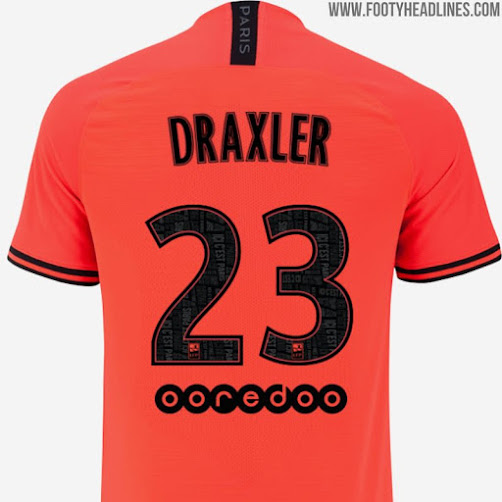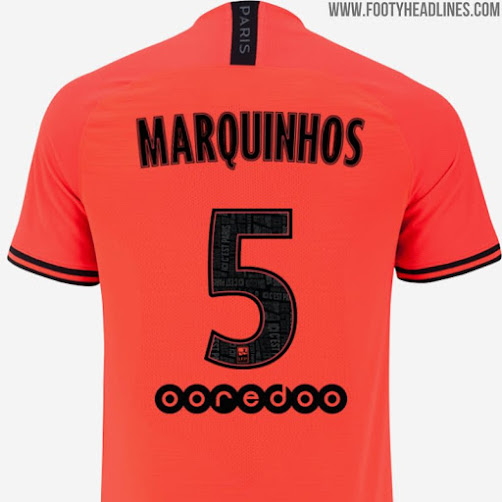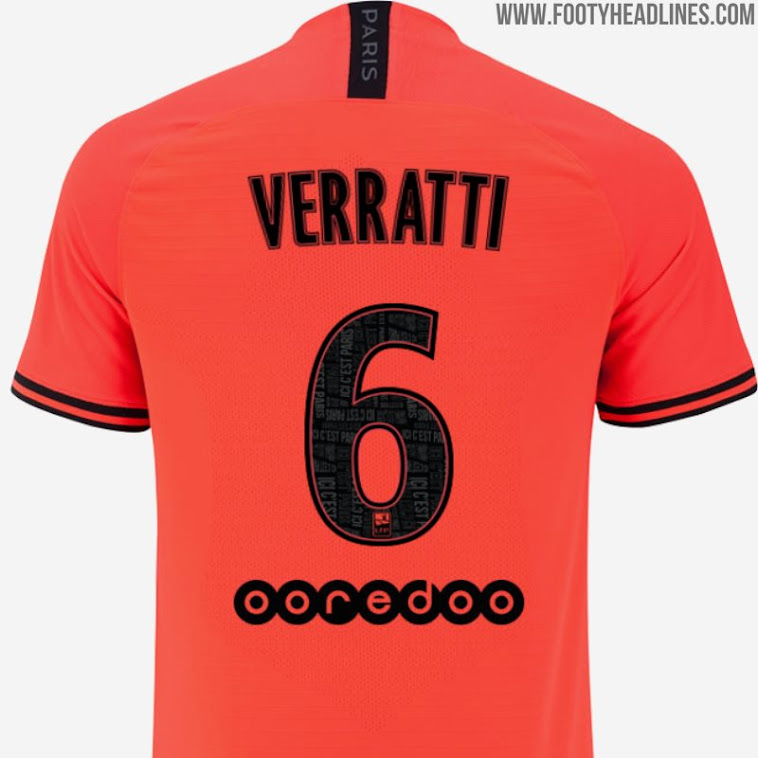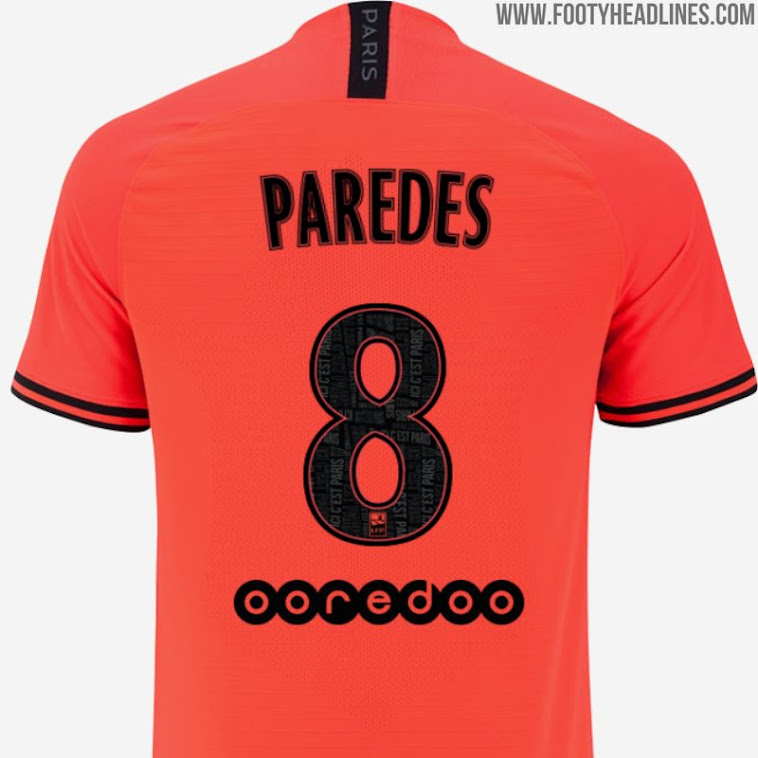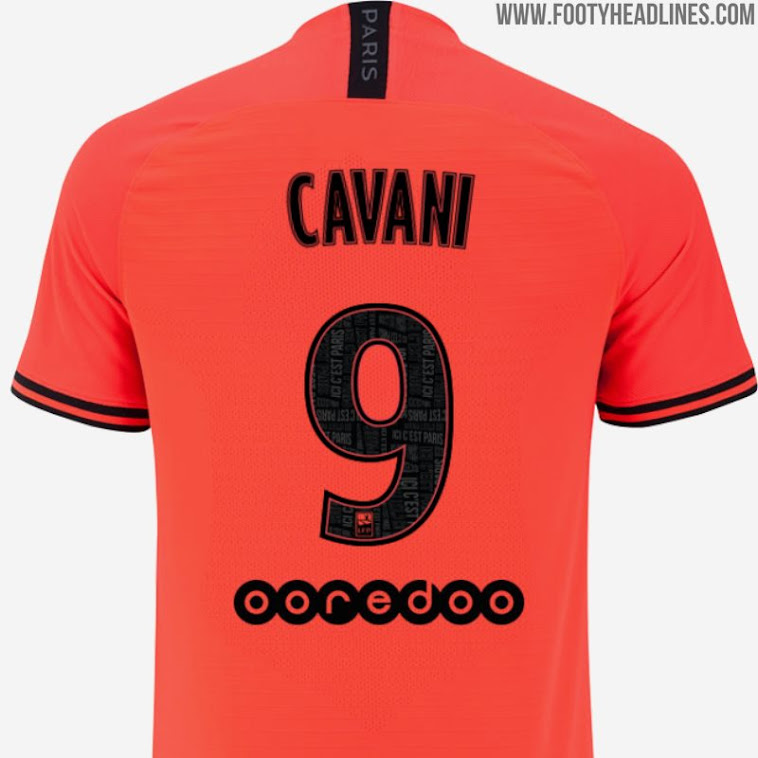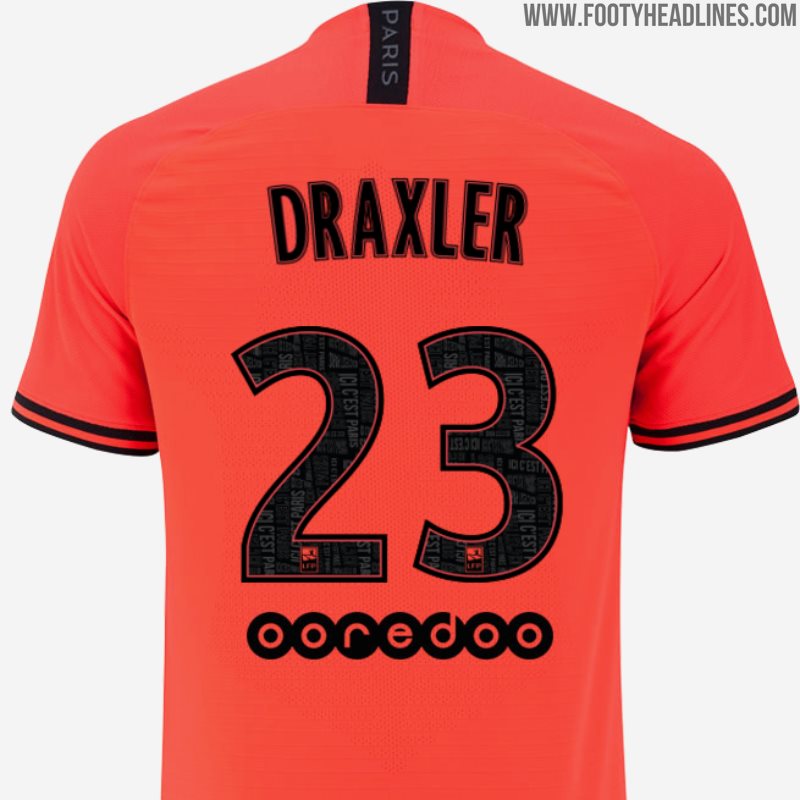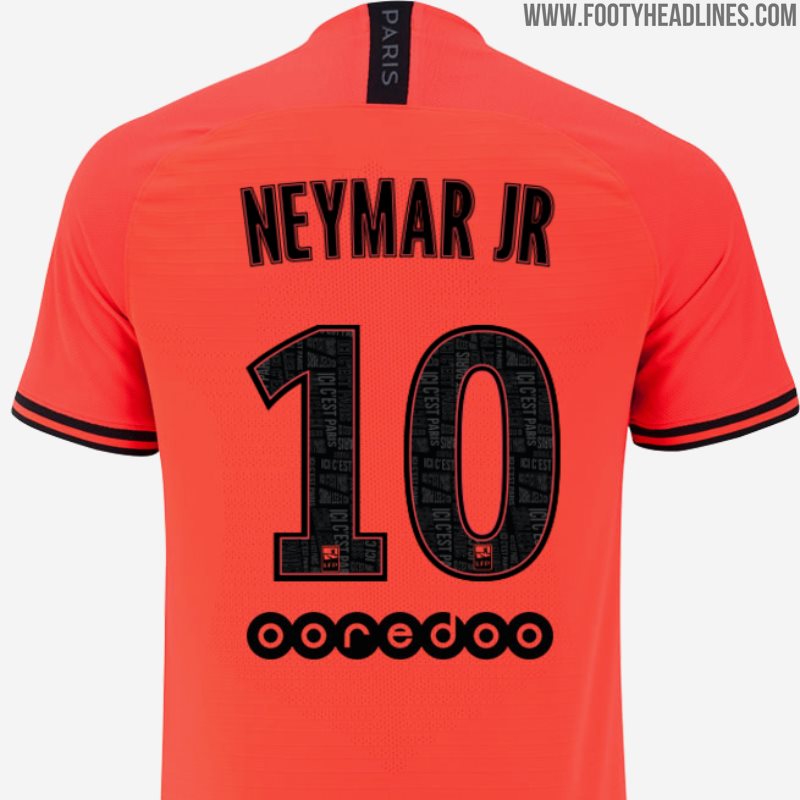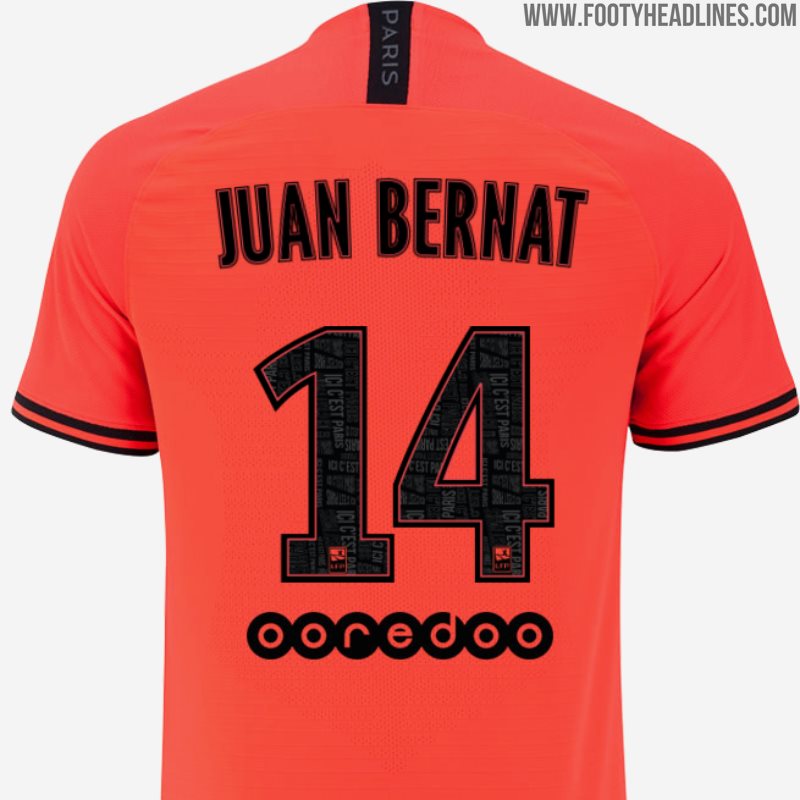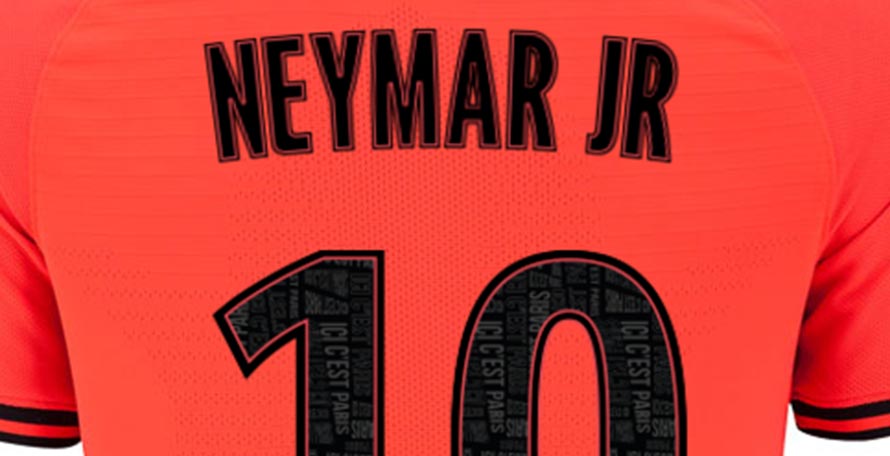
Einzigartige PSG 19-20 Auswärtstrikot-Schriftart Enthüllt
PSG hat kürzlich ihr neues Auswärtstrikot 2019/20 vorgestellt, das Teil der laufenden Zusammenarbeit mit Jordan ist.
PSG 19-20 Auswärtstrikot-Schriftart
Dies ist das PSG 2019-20 Trikot von Neymar.
Für die PSG 19-20 Schriftart hat Paris Saint-Germain eine subtile Textgrafik hinzugefügt, die aus dem Clubmotto "Ici c'est Paris" (Dies ist Paris) besteht.
Obwohl es in der französischen ersten Liga eine ligaweite Schrift gibt, können Vereine in der Liga ihr eigenes Muster hinzufügen.